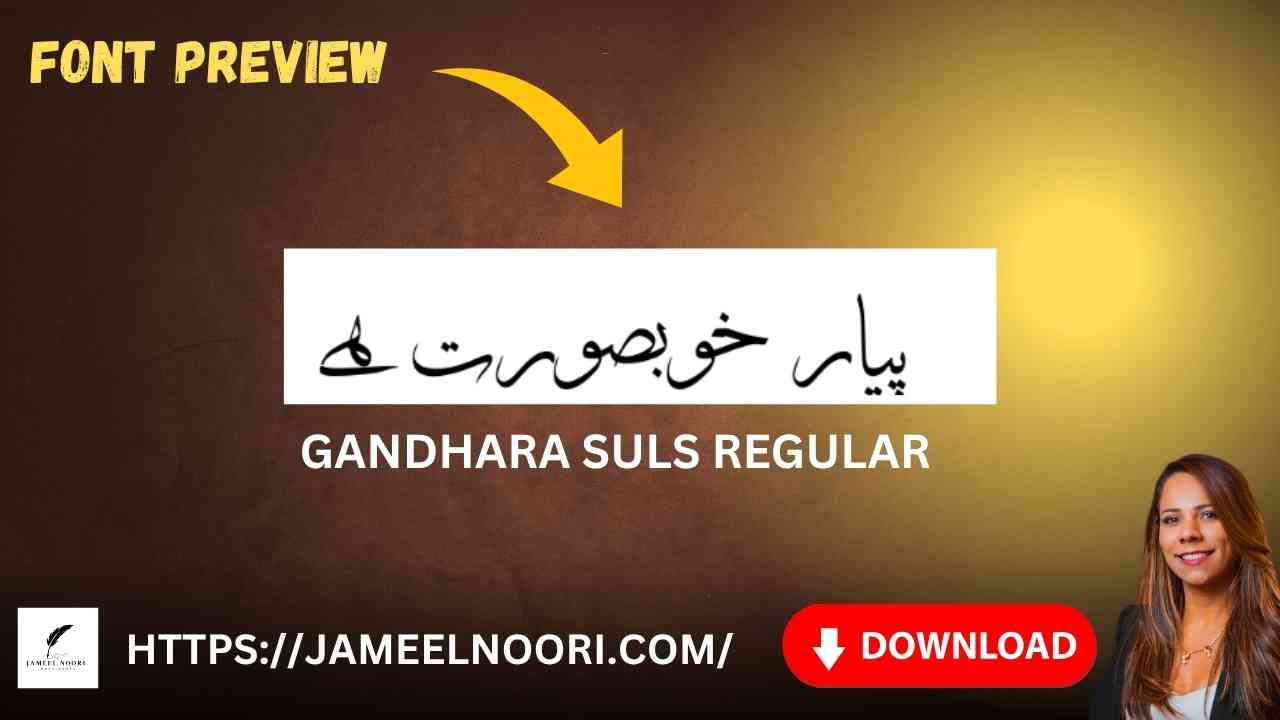
Introduction – Download Urdu font Gandhara Suls Regular for Elegant Urdu Writing
Agar aap Urdu me stylish aur calligraphic text likhna chahte hain, to Download Urdu font Gandhara Suls Regular aap ke liye perfect choice hai. Yeh font ek Regular TrueType font hai jo Urdu likhne ka ek royal aur artistic touch deta hai. Pakistan me specially Lahore, Karachi aur Islamabad ke designers aur calligraphers is font ko extensively use this font.
Download Urdu font Gandhara Suls Regular ki Key Features & Specs
| Recommended Use | Books, Islamic calligraphy, Flyers |
Where to Use Download Urdu Font Gandhara Suls Regular
Download Urdu font Gandhara Suls Regular ka use kai jagahon par hota hai, khas tor par:
- Urdu Calligraphy Projects
- Religious or Islamic Publications
- Wedding Cards aur Invitations
- Poetry aur Shayari Design
- YouTube Thumbnails in Urdu
Ye font un logon ke liye ideal hai jo bold aur royal style me Urdu likhna chahte hain.
Why Download Urdu font Gandhara Suls Regular is Expert Choice for Designers in Pakistan
Pakistan me bohat se freelancers, calligraphers aur designers har roz Download Urdu font Gandhara Suls Regular use kar rahe hain. Yeh font unka favorite is liye hai:
- Kyun ke iski line weight aur curves bohat artistic hain
- Is font se likhe gaye lafz har screen par crisp aur readable nazar aate hain
- Ye font har graphic design ka professional touch barhata hai
Top 5 Benefits
- Elegant and artistic Urdu calligraphy
- Best for Islamic, poetic, and wedding content
Agar aap stylish aur artistic Urdu calligraphy ka shauq rakhte hain, to Gandhara Suls Regular aap ke liye behtareen font hai. Iska unique design aur high-quality curves isay Arabic aur Urdu dono me khubsurat banata hai. 2025 me ye font na sirf graphic designers balki publishers aur students ke liye bhi ek must-have resource hai. Isay download karke aap apne projects me professional aur elegant touch de sakte hain.